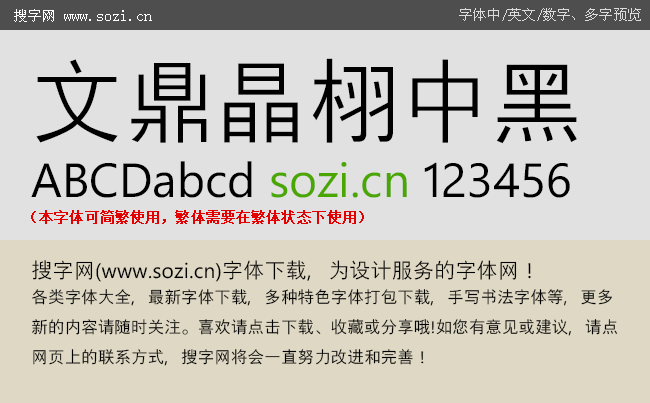
文鼎晶栩中黑(ARCrystalzhonghei)
文鼎晶栩中黑體字體是是搜字網(wǎng)提供一款免費(fèi)中文字體下載。其特點(diǎn)是比較傳統(tǒng)的黑體,瘦長(zhǎng),不如蘭亭黑那么飽滿,橫豎沒(méi)有喇叭口,撇捺有輕微的喇叭口,在小字號(hào)表現(xiàn)不錯(cuò),歡迎下載!